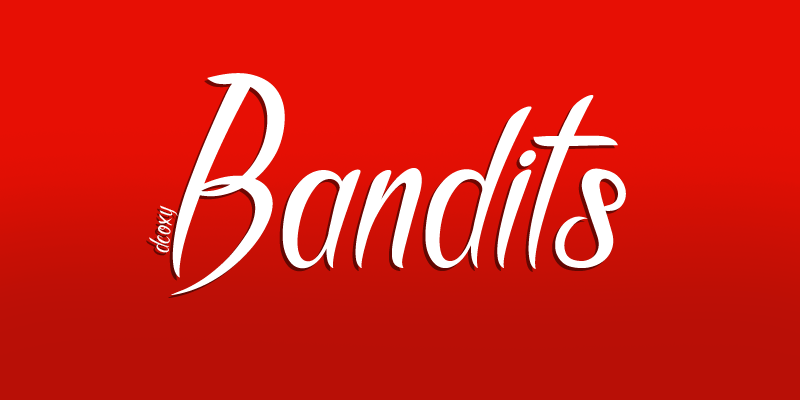
A Bandits Font é uma cálida e suave escrita a mão que se destaca nas categorias de fontes manuscritas. Criada pelo designer Hamilton, esta fonte oferece um toque casual e vibrante que combina perfeitamente com qualquer projeto que você deseje personalizar em sua marca ou projeto gráfico. Com uma aparência elegante e autêntica, a Bandits Font é ideal para anúncios, logotipos de marcas, design editorial e até mesmo materiais publicitários que desejam um toque único. Embora seja uma fonte manuscrita, o resultado final não perde a rigidez necessária para transmitir eficácia ao texto. Seu uso correto pode tornar qualquer projeto notável sem comprometer seu impacto informativo ou convencional. Como em todas as coisas, é importante lembrar que uma licença é necessária para qualquer aplicação comercial ou promocional da Bandits Font. Para mais informações sobre como adquirir essa incrível fonte, contate Hamilton diretamente no endereço de email .